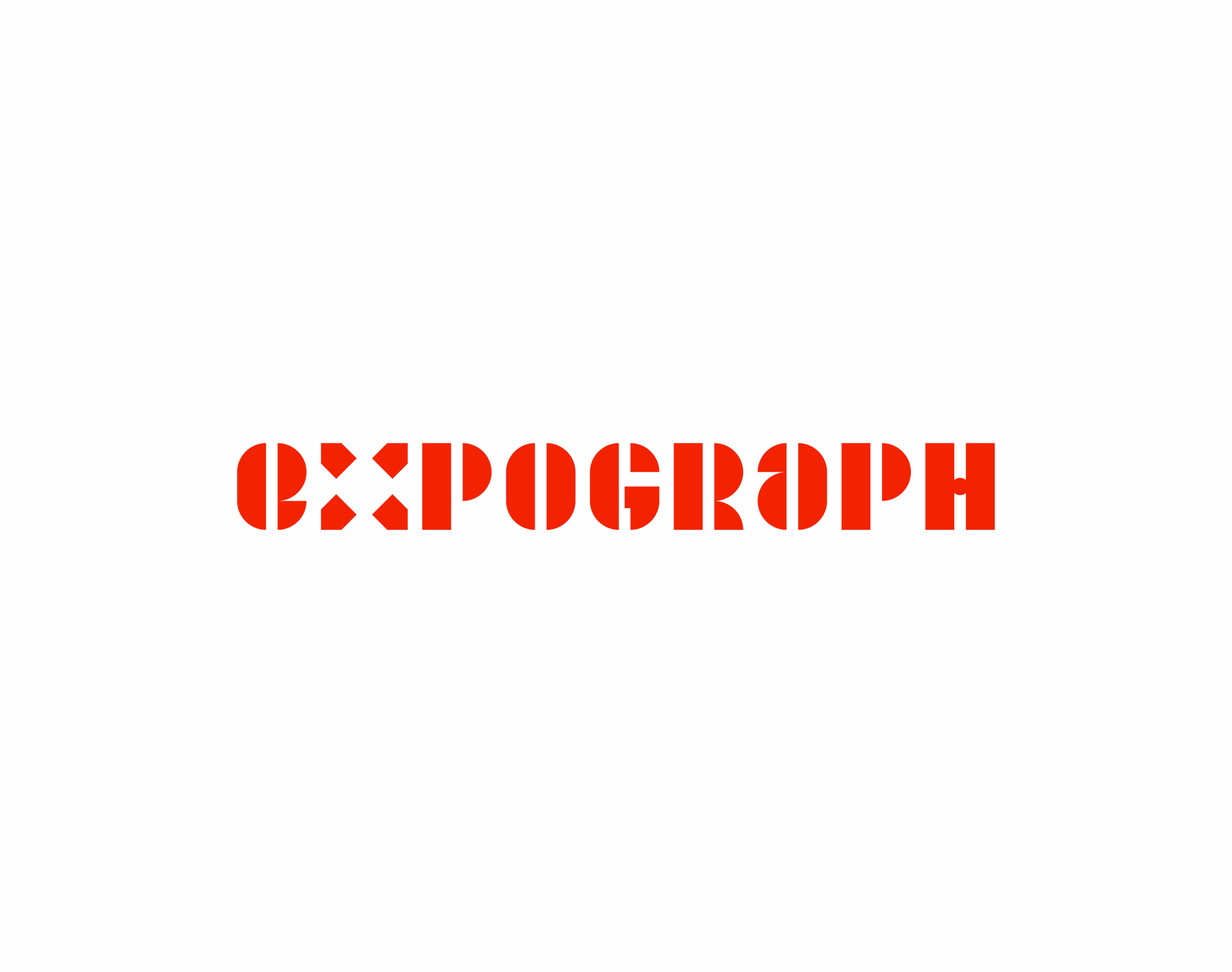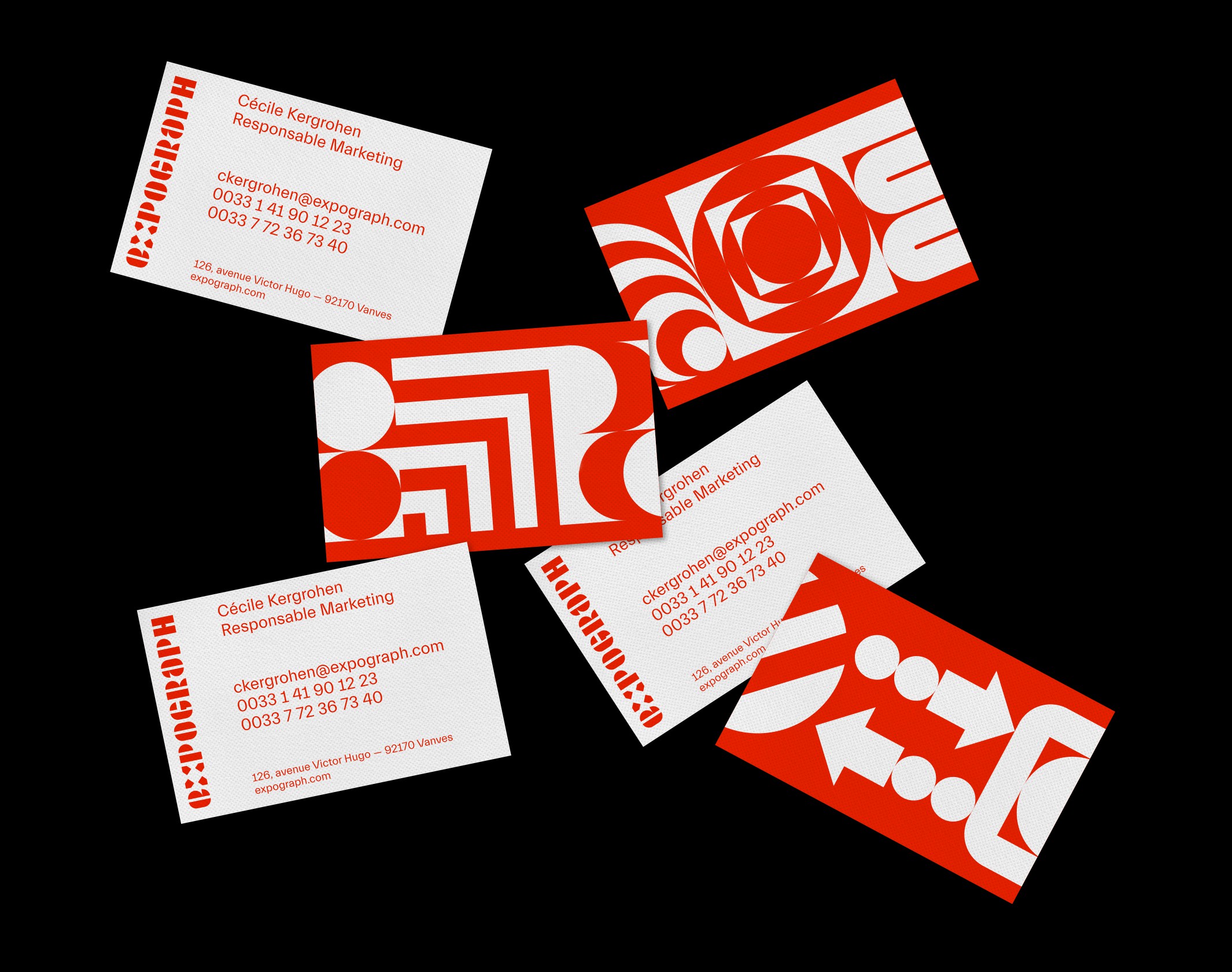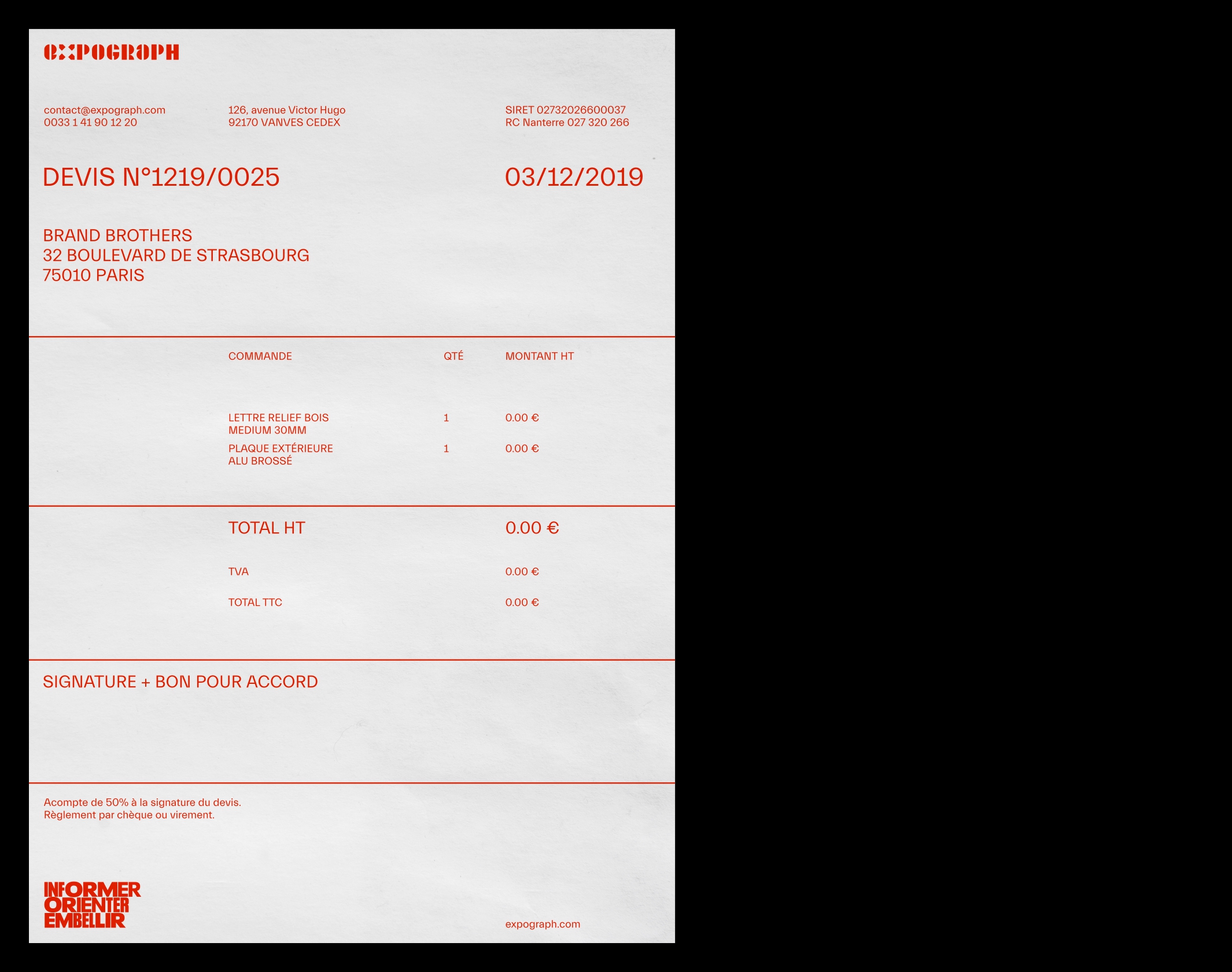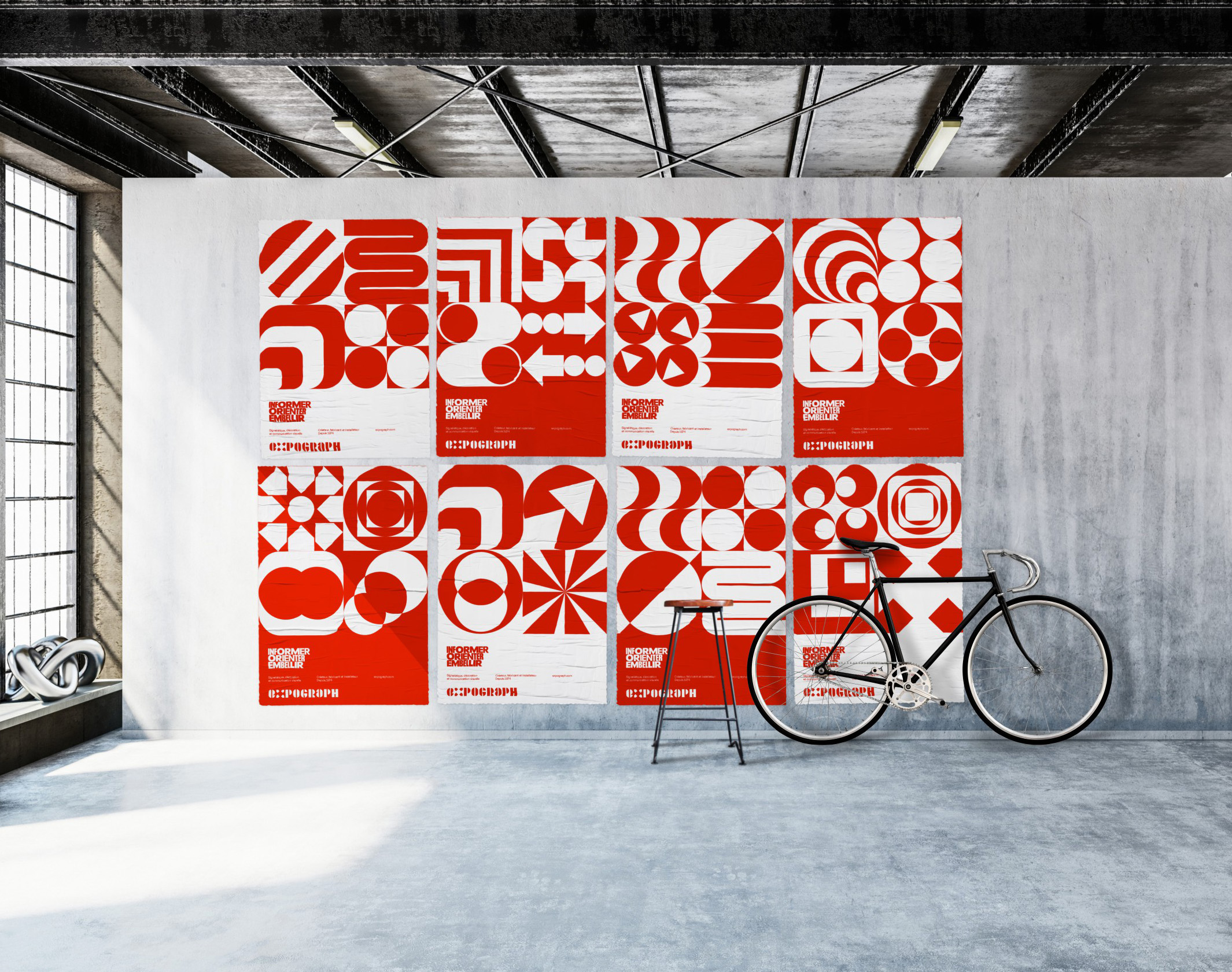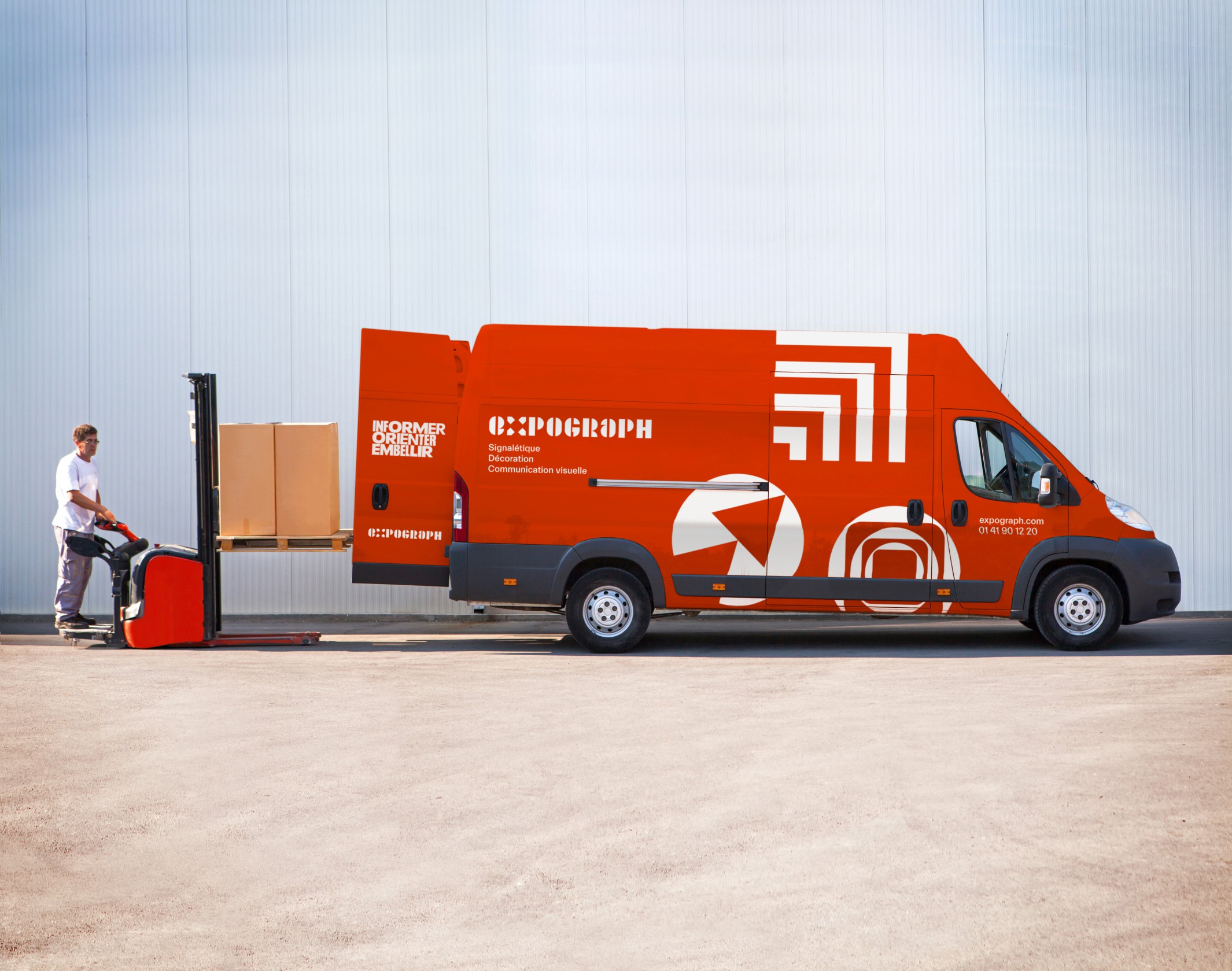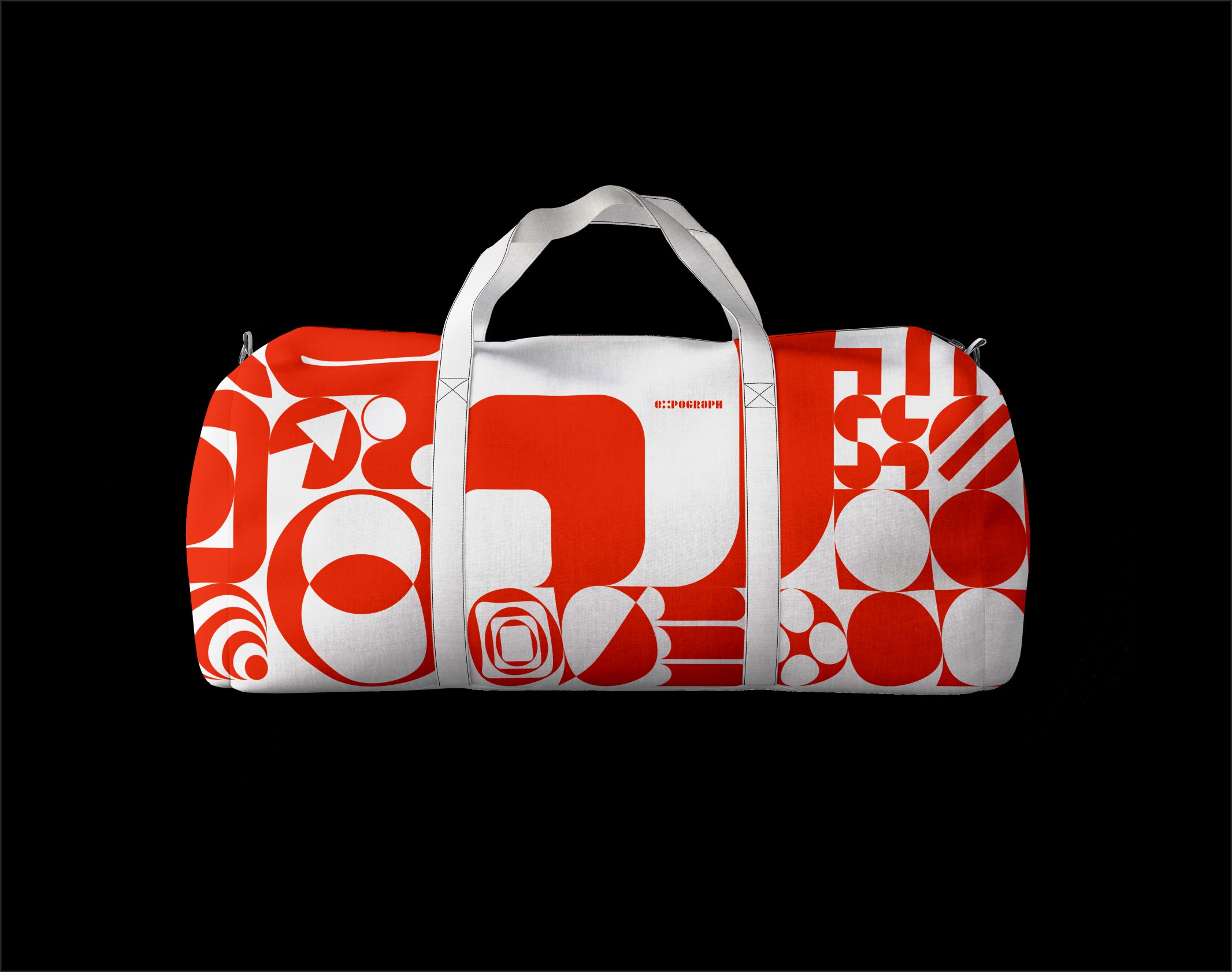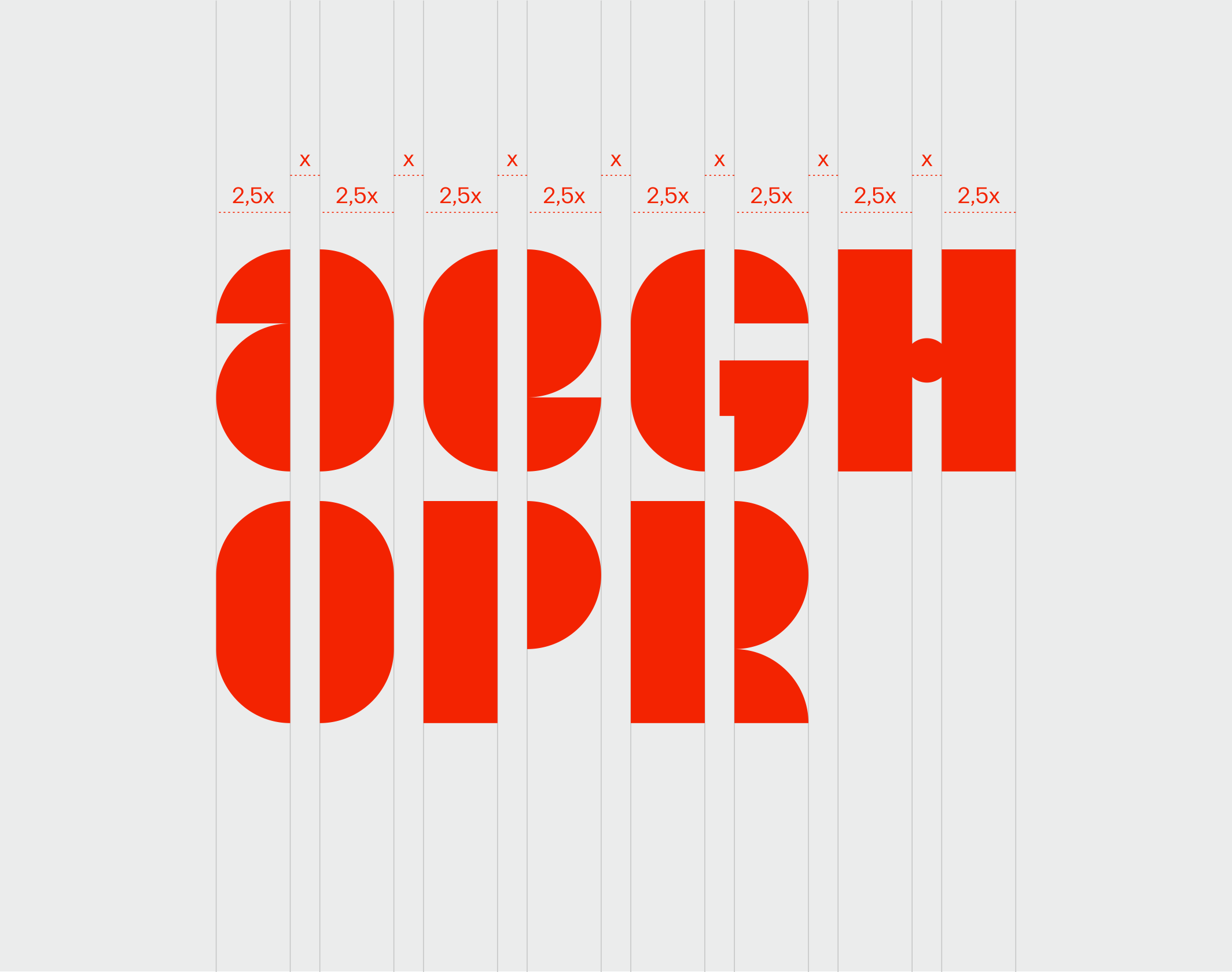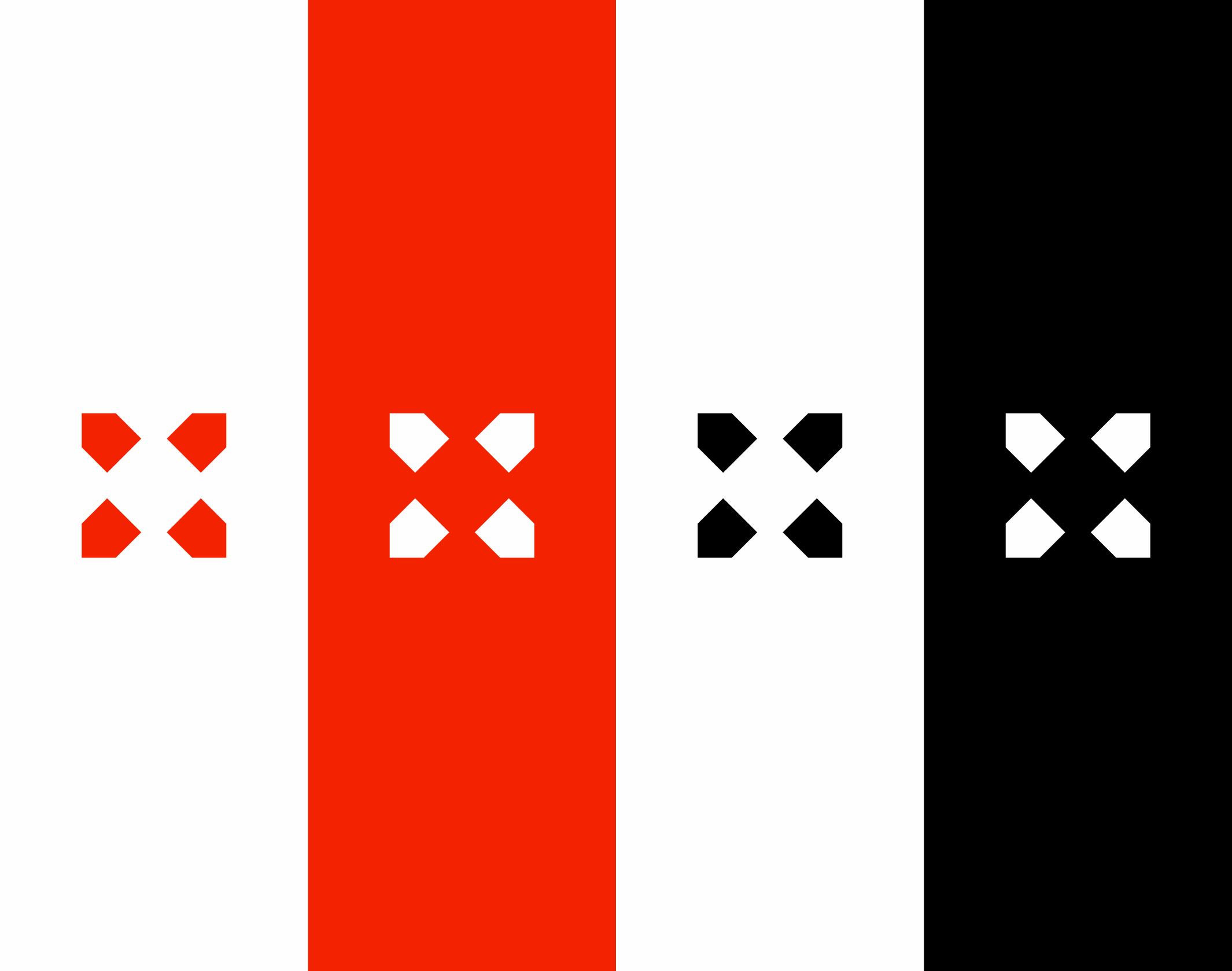
Expograph
Expograph a radicalement transformé son identité visuelle pour mieux refléter son expertise en signalétique, alliant technicité et esthétique moderne
Expograph est un des acteurs majeurs de la signalétique en France. Implanté depuis 1973 aux portes de Paris, le groupe se spécialise en conception et fabrication de systèmes de signalétique, en communication visuelle et décoration. Enseignes, lettres relief, marquage de bâtiments et de locaux ; l’entreprise, qui pense et réalise l’ensemble de ses produits en interne, revendique un savoir-faire désormais. Au printemps 2019, nous avons été mandatés pour repenser intégralement l’identité visuelle. Leur mantra : informer, orienter, embellir.
Nous avons de suite, de concert avec l’équipe communication, recentrer l’approche vers un axe plus radical, plus direct, plus brut, en exprimant la technicité et la pensée systémique à travers leur identité graphique. Le nouveau logo, basé sur un design typograhique maison, est un typogramme monochromatique, dont les caractères ont été conçus sur la base d’une série de rectangles identiques. Le « X », poitant vers quatre directions, devient le point de départ du nouveau système visuel : une collection de formes, que nous enrichissons de manière permanentes, qui s’assemblent à l’infini et évoquent par un biais subtil les trois grandes promesses de l’entreprise. Les multiples déclinaisons s’étendent du print aux véhicules ; le nouveau site internet, quant à lui, sera mis en service d’ici la fin de l’année 2019.